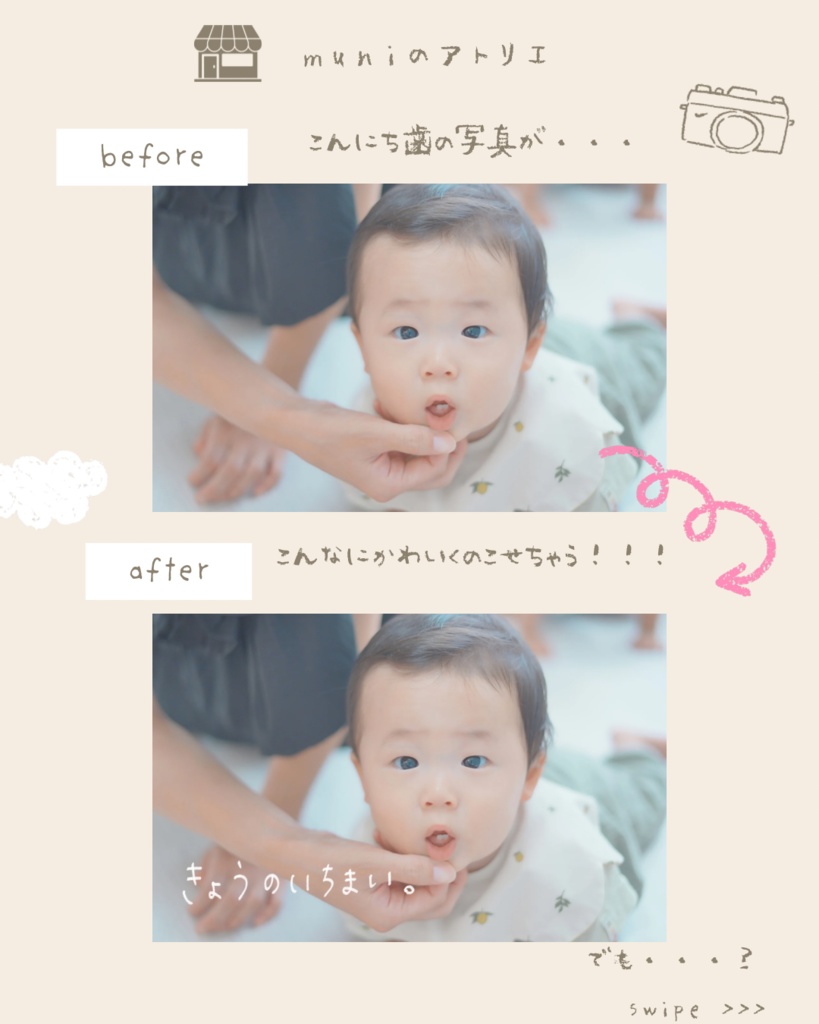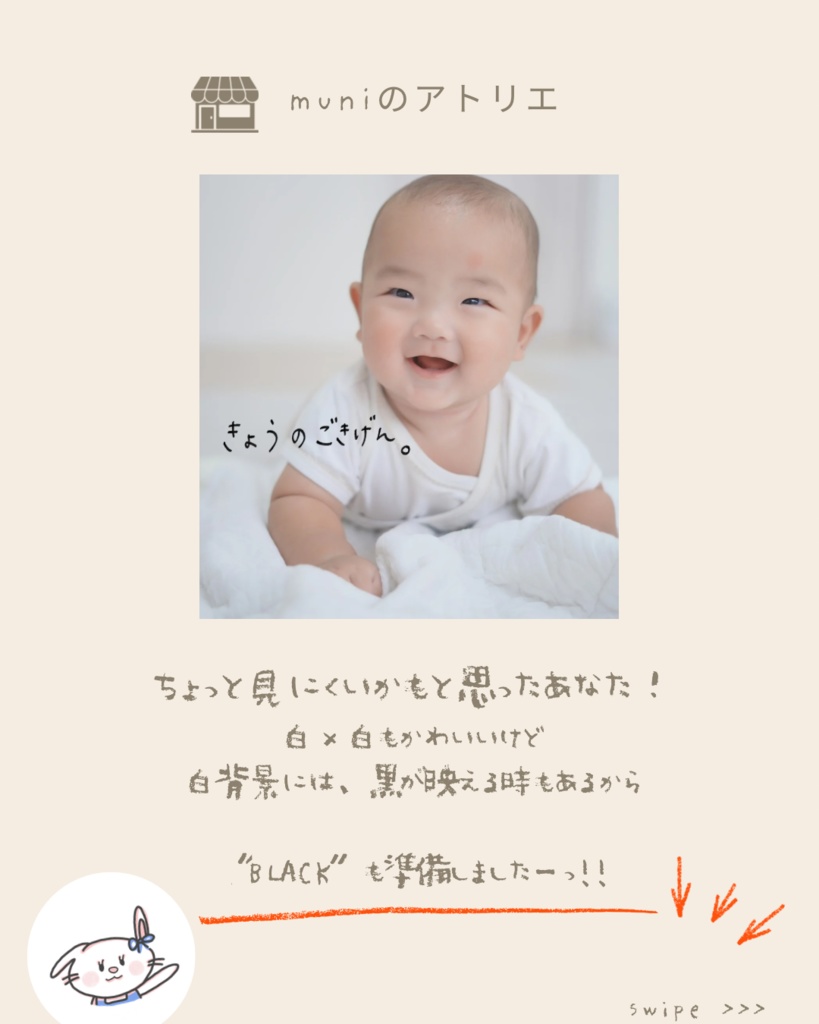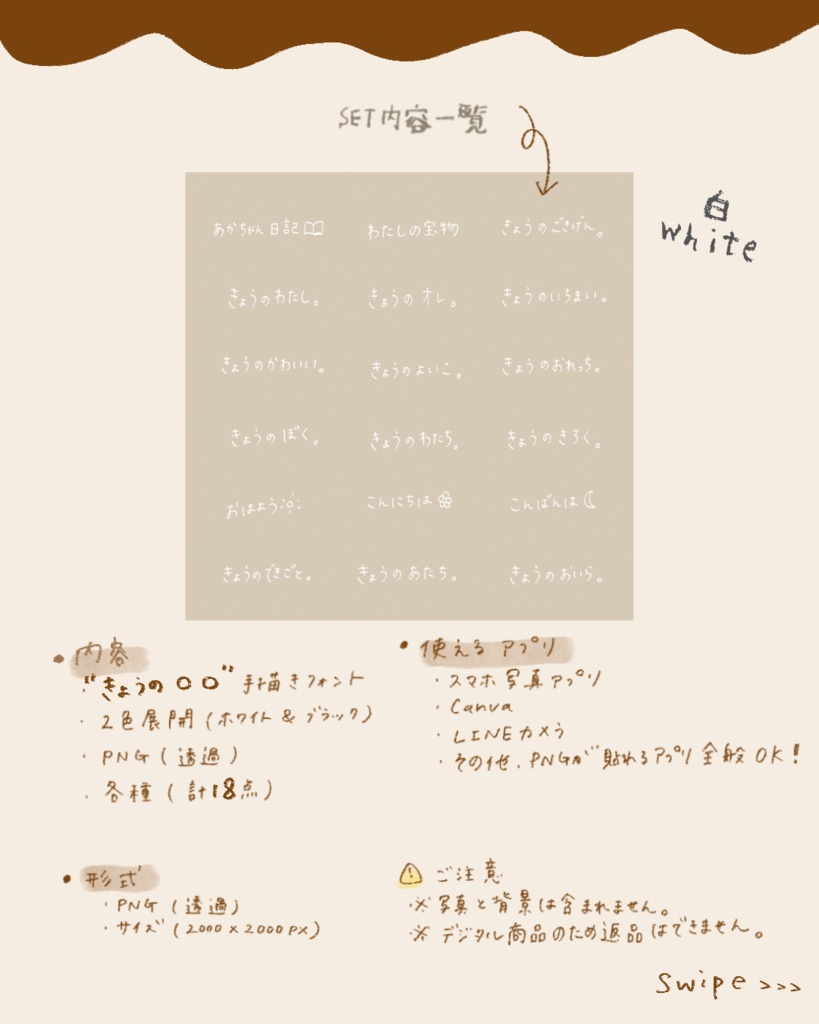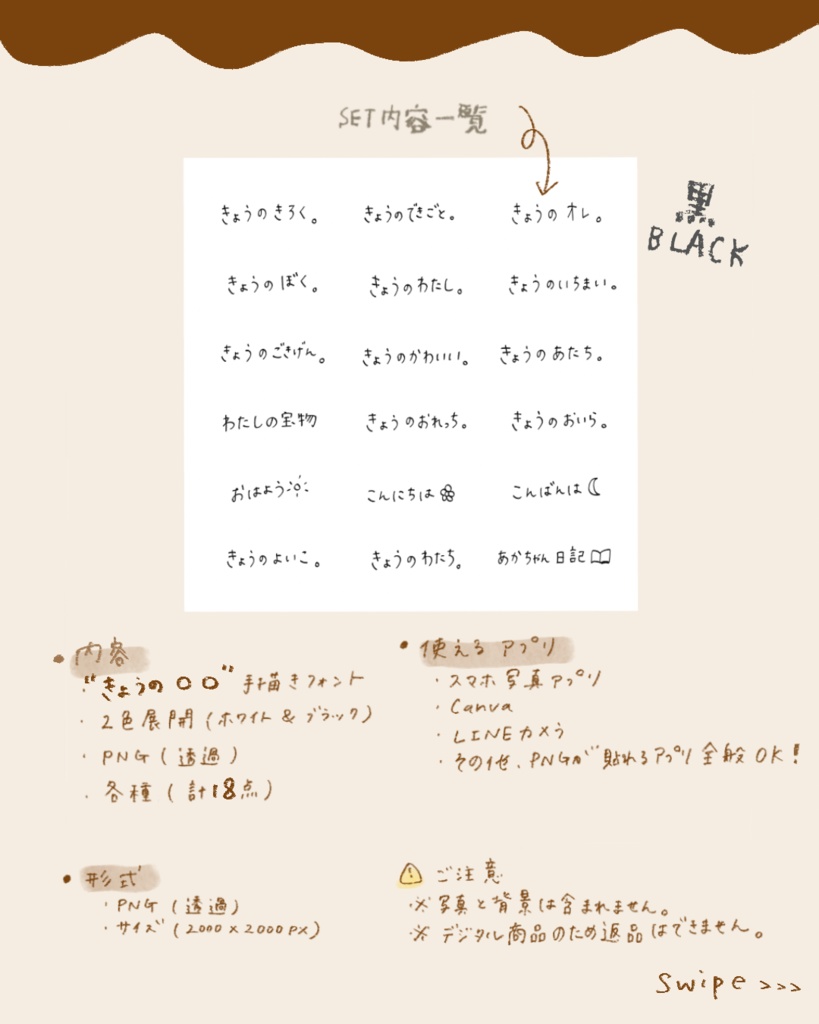
きょうのシリーズ手描きフォントセット(全36種/白&黒/PNG)|Today’s Daily Words Font Set
ようこそ muni のアトリエへ 🐰🎀 リボンうさぎの店長 “むに” がつくった、 毎日の “きょう” をかわいく残すための手描きフォントセットです。 ⸻ Welcome to muni’s Atelier 🐰🎀 This is a soft, hand-drawn word set designed to make your baby’s daily photos even more precious.
• “きょうの〇〇” 手描きフォント • 2色展開:白/黒 • PNG(透過) • 18ワード × 2色=全36点 • 写真にそのまま貼るだけで使えます✨ ⸻ 📦 What’s included • 18 hand-drawn “Today’s ___” phrases • White & Black versions • PNG format(transparent) • 36 files total • Just place them on your photo & it’s ready ✨
for) • 毎日の写真をかわいく残したい • シンプルで“ふんわり系”の世界観が好き • スマホだけで手軽に加工したい • 白背景/暗め背景どちらにも使える文字がほしい • 兄弟・家族の “きょう” を統一感あるデザインで残したい ⸻ Perfect for • Moms & dads who want cute daily memories • Parents who love natural, soft designs • Anyone who wants easy photo decoration • Instagram baby-photo lovers • Families who want matching “Today’s ___” captions